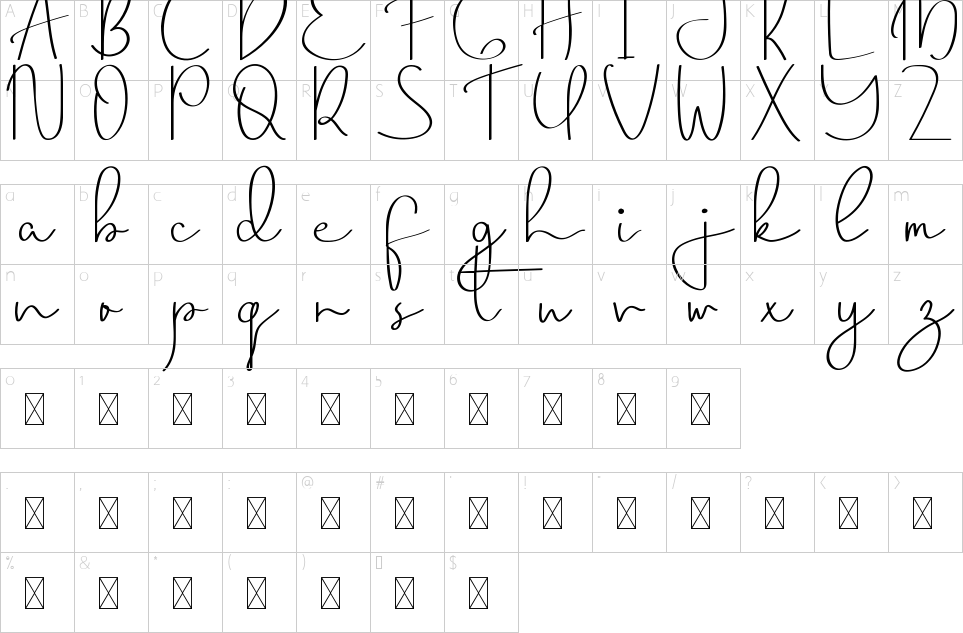
Aqui está uma descrição em português do Brasil, envolvente e natural, para uma página de download da fonte ‘Mile Green Font | 1001 Free Fonts’: Mile Green é uma elegante e sofisticada fonte de texto que combina facilmente qualquer design gráfico. Seu estilo minimalista e alegre faz dele um excelente candidato para usar em um grande número de projetos digitais, desde aplicativos móveis até sites modernos. Desenvolvida por EdricStudio, a fonte ‘Mile Green’ já foi baixada 3.464 vezes. O uso desta fonte é absolutamente livre, permitindo que você personalize suas criações sem preocupações de direitos autorais. Se você está procurando por uma fonte clara e moderna para seus projetos gráficos, não há melhor escolha que Mile Green. Baixe-a agora e inspire-se com seu design moderno e versátil.